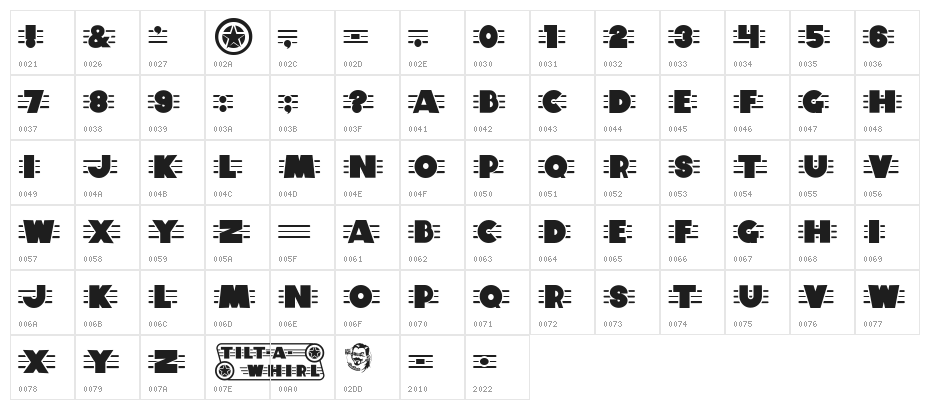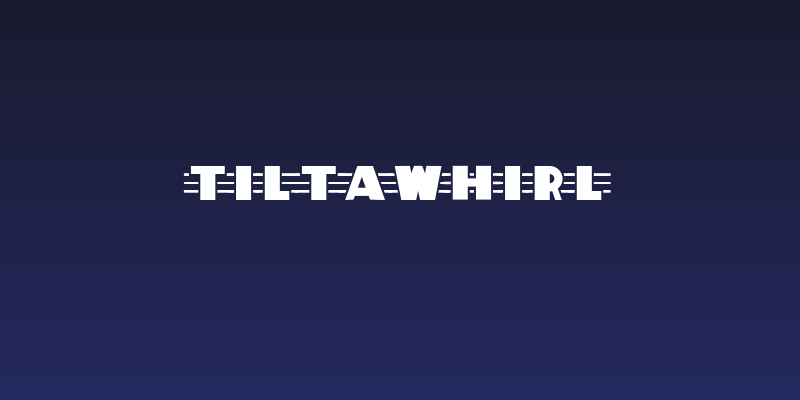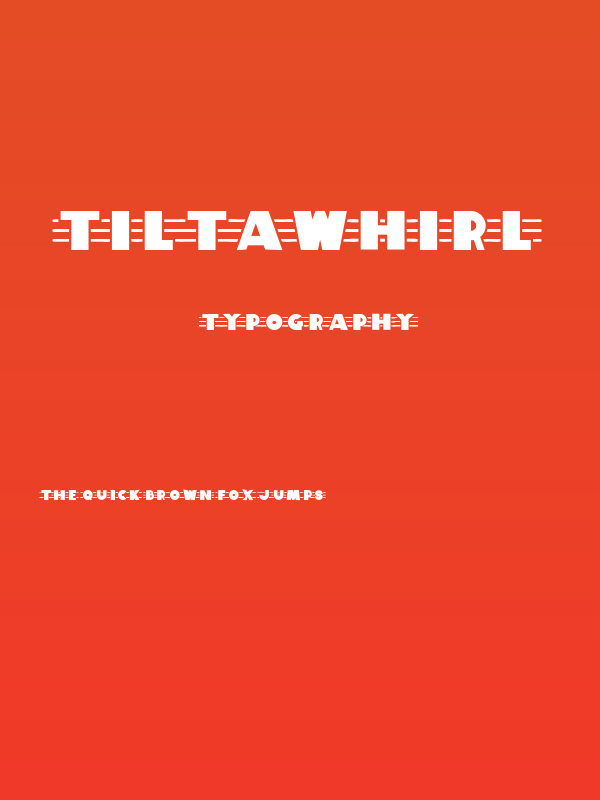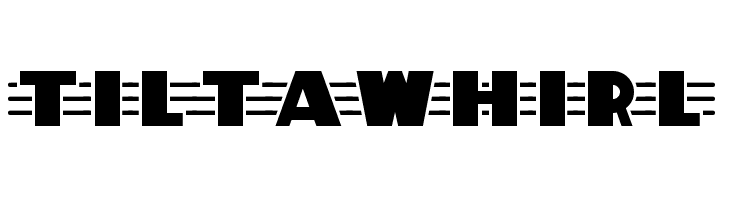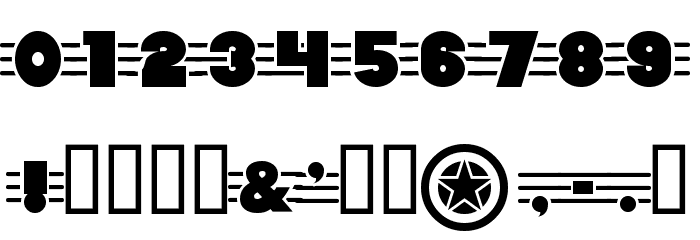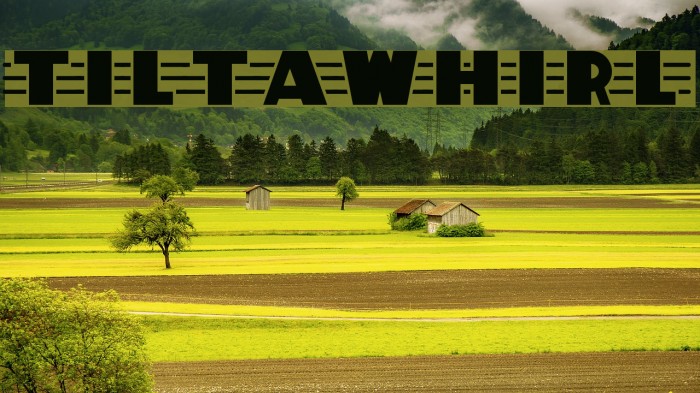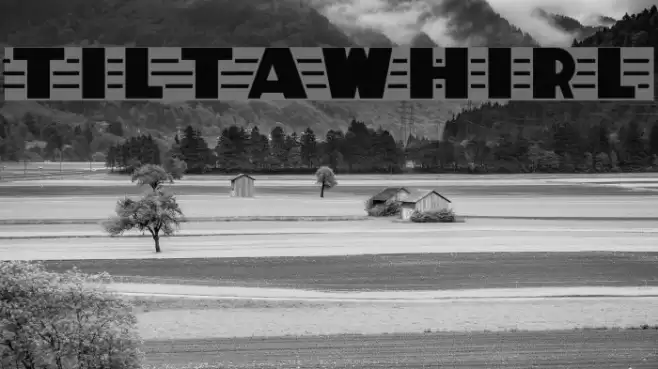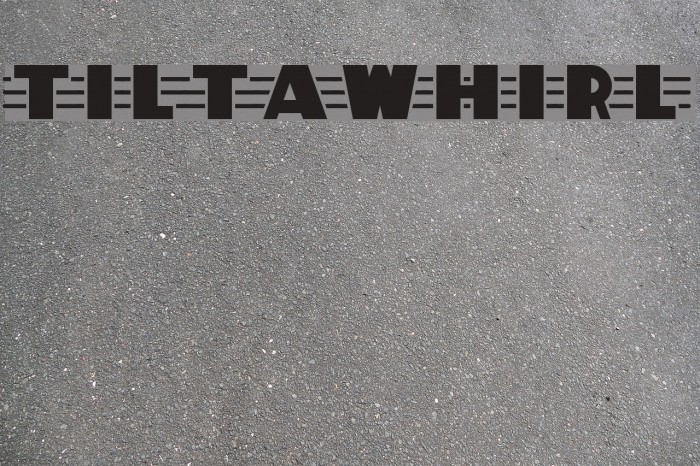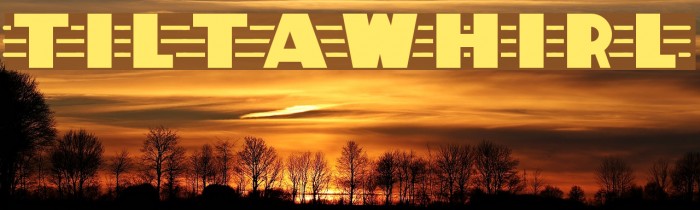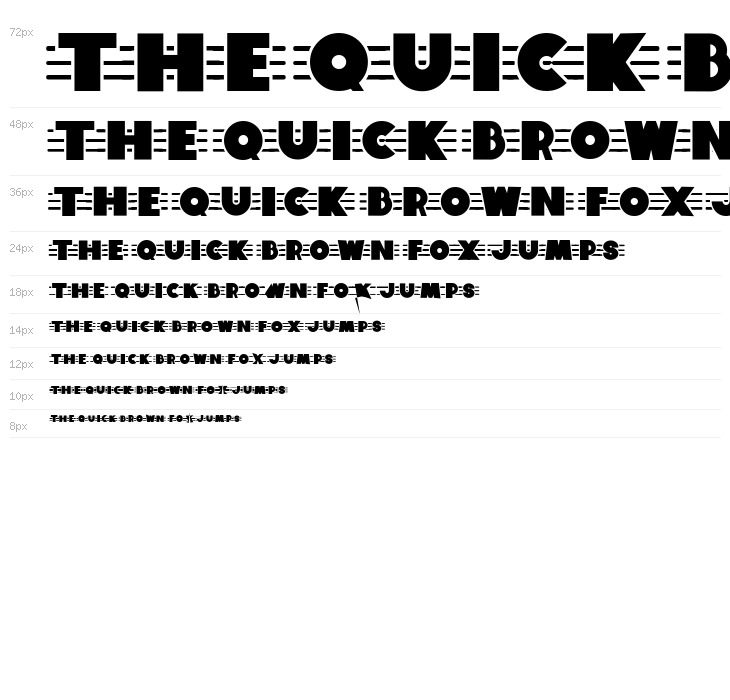
TiltAWhirl Font
Fonts by Daniel Gauthier
| النمط العام | Vintage |
| مشاريع مقترحة | Ideal for retro-themed posters, amusement park branding, vintage advertisements, and playful graphic designs. |